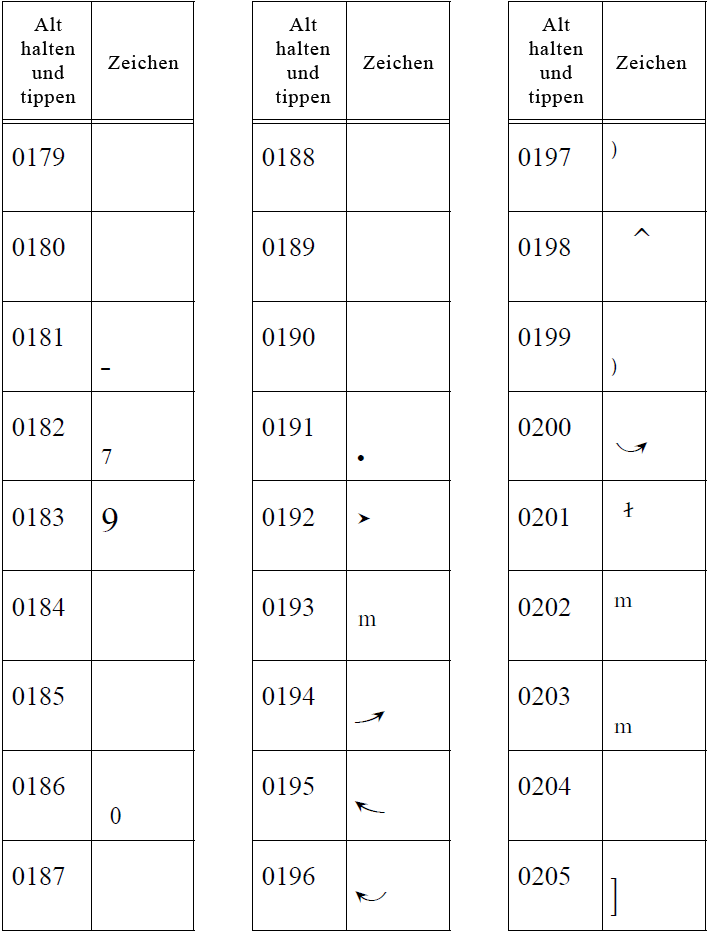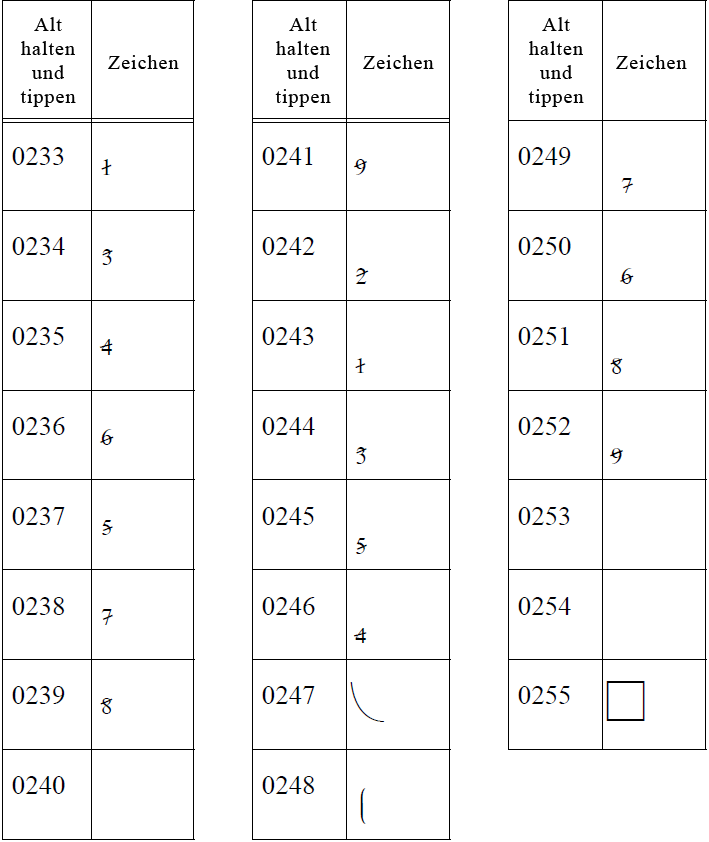
Dieser Zeichensatz enthält Ziffern und Symbole, die sich übereinander platzieren, z. B. für Generalbass oder harmonische Analyse. Dieser Zeichensatz wird für die Anzeige von Dokumenten, die mit Finale erstellt wurden, benötigt.
Hinweis. Diese Liste enthält die am häufigsten verwendeten Symbole und Tastenkürzel. Eine komplette Liste aller Symbole des Zeichensatzes Finale Numerics finden Sie in der Zeichentabelle Ihres Betriebssystems.